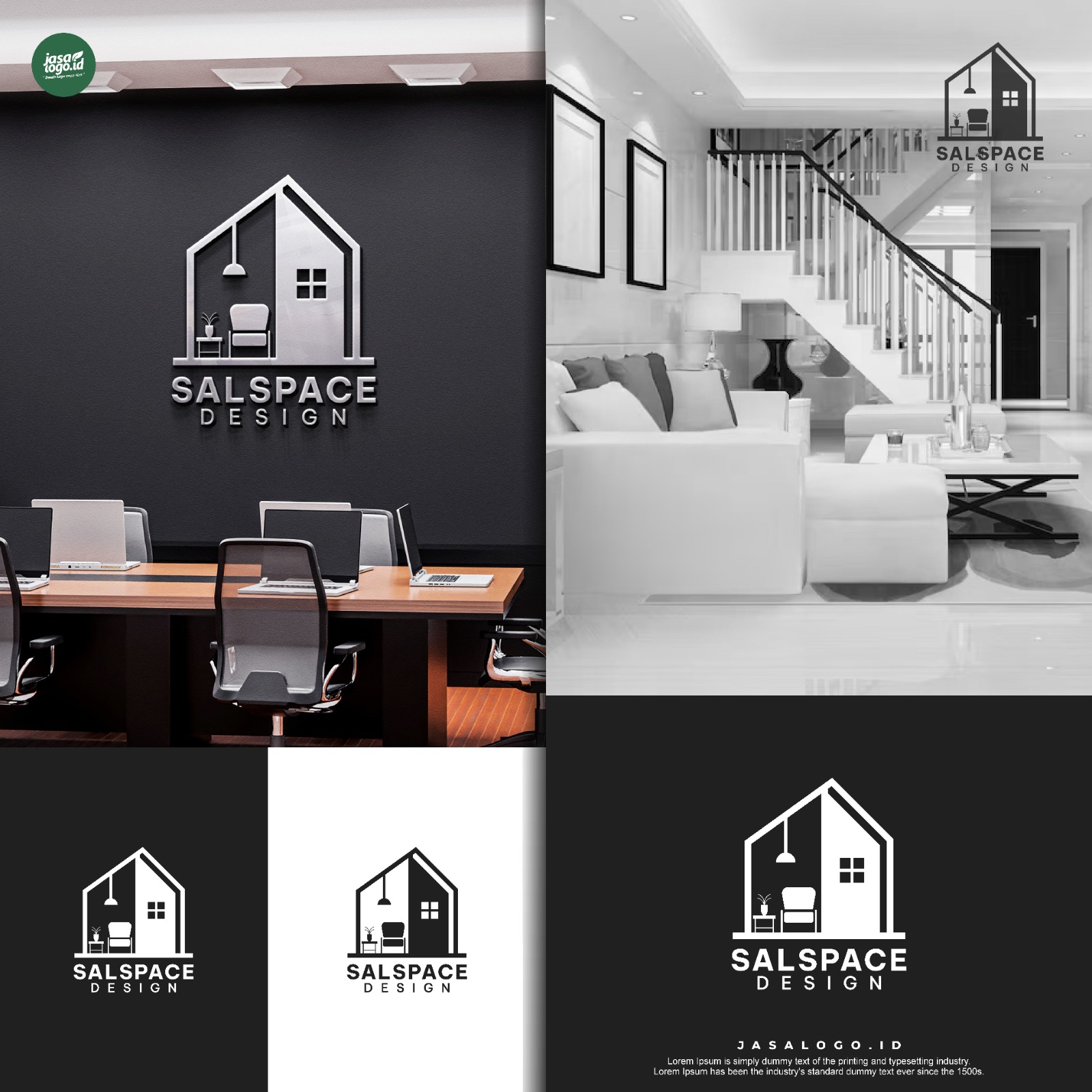
Dalam media digital, desain branding perlu memiliki desain yang sederhana dan fleksibel. Termasuk dalam pemilihan gaya tipografi juga harus sederhana agar mudah dibaca dan jelas dalam berbagai media. Kombinasi sesama font sans serif dalam desain logo memiliki kekuatan untuk tampil modern, minimalis dan fleksibel.
Desain logo bisa memiliki kombinasi dua font sans serif karena ada banyak jenis font sans serif dengan berbagai style. Kombinasi dua font sans serif dengan membedakan gaya huruf, ukuran dan jenis fontnya. Kombinasi sesama font sans serif akan memastikan logo memiliki keterbacaan yang baik.
KELEBIHAN KOMBINASI FONT SANS SERIF DALAM DESAIN LOGO
Jika dipilih dengan tepat, kombinasi sesama font sans serif sekalipun akan menciptakan kontras dan hirarki visual. Bedakan jenis gaya huruf seperti light, bold atau italic agar menciptakan kombinasi berbeda. Kombinasi sans serif dalam logo memiliki beberapa kelebihan.
Tampilan Modern dan Bersih
Salah satu kelebihan kombinasi sesama font sans serif yaitu menciptakan desain yang bergaya modern dan bersih. Font sans serif memiliki bentuk huruf yang sederhana dan bersih. Untuk itu penggunaan font sans serif digunakan pada brand teknologi dengan kombinasi huruf tipis dan tebal agar tampil sederhana dan kontras.
Konsistensi Visual yang Kuat
Kombinasi dua font sans serif sama-sama tidak memiliki serif dan memiliki desain huruf yang sederhana. Font akan memiliki huruf yang seragam, rapi dan harmonis ketika dipasangkan. Penggunaan cocok untuk brand yang ingin memiliki desain logo berkesan profesional, tanpa berkesan berlebihan.
Fleksibel untuk Digital dan Cetak
Dengan menggunakan kombinasi font sans serif akan memudahkan logo dibaca pada berbagai media digital dan cetak. Penting untuk logo fleksibel agar mudah dibaca dan membangun identitas yang kuat pada beberapa jenis desain. Terutama untuk desain UI/UX, font sans serif cukup efektif untuk fleksibel dan mudah dibaca.
Mudah Dikombinasikan Berat atau Gayanya
Kombinasi sesama font sans serif dapat menciptakan tampilan kontras tanpa perlu menggunakan jenis font sans serif berbeda. Untuk menciptakan hirarki visual, bedakan berat atau gaya fontnya, mainkan gaya huruf tebal, regular, italic dan tipis. Kombinasi font sans serif italic tebal dan font tipis akan menciptakan kontras meski dari font yang sama.
Menciptakan Hirarki Visual Tanpa Mengganggu Kesatuan
Dengan kombinasi sesama font sans serif yang mirip akan menciptakan kombinasi harmonis. Teks nama brand dan tagline bisa menggunakan satu font sans serif sehingga tidak menciptakan bentrok gaya. Font tetap bisa dibuat berbeda tanpa mengganggu kesatuan visual.
CONTOH LOGO DENGAN KOMBINASI SESAMA FONT SANS SERIF
Desain logo banyak menggunakan kombinasi sans serif sehingga memudahkan nama brand dibaca dan menciptakan desain modern. Logo dengan font ini akan memiliki desain minimalis dan bersih. Berikut beberapa contoh logo dengan kombinasi sesama font sans serif yang harmonis.
Logo Caramel Cafe & Donut
Pada desain logo tersebut kombinasi font sans serif membuat nama brand mudah dibaca dan tampil sederhana. Logo memiliki kombinasi dua jenis font sans serif berbeda sehingga menciptakan gaya yang kontras. Font sans serif untuk nama brand memiliki gaya huruf yang tidak begitu tajam.
Teks nama brand menggunakan gaya huruf sans serif yang tebal sementara taglinenya menggunakan sans serif regular. Perbedaan gaya huruf tersebut menciptakan kontras dalam hirarki visual yang jelas. Tipografi sans serif tebal dan tidak tajam cocok merepresentasikan brand bakery yang ramah.
Logo Twentyone
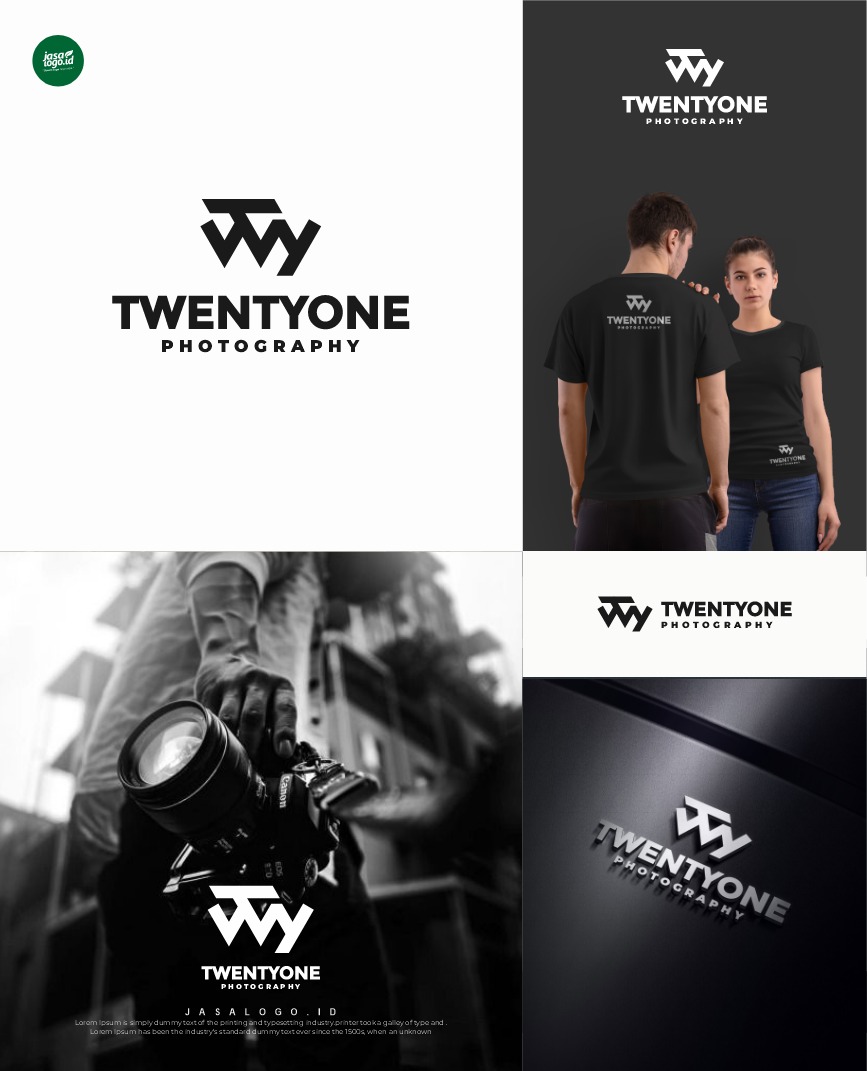
Brand fashion biasanya juga sering kombinasi font sans serif untuk menciptakan kesan stylis dan minimalis. Font sans serif akan membantu nama brand fashion mudah dibaca sehingga mudah pula brand fashion diingat. Logo fashion tersebut menggunakan style sans serif dengan geometris tebal dan lancip.
Gaya font sans serif geometris pada logo memiliki bentuk yang tajam sehingga berkesan premium dan high-end. Dalam desain logo kombinasi font tersebut akan menciptakan kesan logo fashion yang berkualitas. Sementara tipografi tagline dalam logo memiliki font sans serif yang berukuran lebih kecil dan memiliki font tebal sehingga mudah dibaca.
Logo Binamitra
Kombinasi sans serif akan menciptakan logo yang modern, serius dan profesional sehingga cocok untuk logo perusahaan. Kombinasi tipografi pada logo perusahaan menggunakan font sans serif. Gaya huruf geometris menciptakan teks sederhana yang mudah dibaca dan berkesan profesional.
Meski logo memiliki sesama font sans serif yang mirip tetapi memiliki berat berbeda dan ukuran yang kontras. Font sans serif dalam logo perusahaan akan menciptakan kesan perusahaan yang profesional dan tegas.
Logo Koperasi Pemasaran
Untuk menciptakan kontras dari kombinasi font sans serif selain membedakan gaya huruf dan berat terkadang juga bisa menggunakan warna. Logo tersebut juga memiliki kombinasi sans serif yang sederhana sehingga mudah dibaca. Font menciptakan tipografi sederhana yang memberi kesan logo profesional.
Brand Arsitektur dan Interior
Biasanya logo arsitektur dan interior akan memiliki style geometris sehingga cocok dengan kombinasi sesama san serif. Desain akan tampil rapi dan seimbang sehingga menciptakan estetika profesional.
Kombinasi font sans serif bisa menjadi pilihan jika ingin menciptakan desain yang sederhana, minimalis dan modern. Terutama dengan sans serif gaya geometris akan menciptakan tampilan huruf yang tajam sehingga berkesan profesional. Kombinasi font tersebut juga efektif menciptakan desain logo yang sederhana dan mudah dibaca.